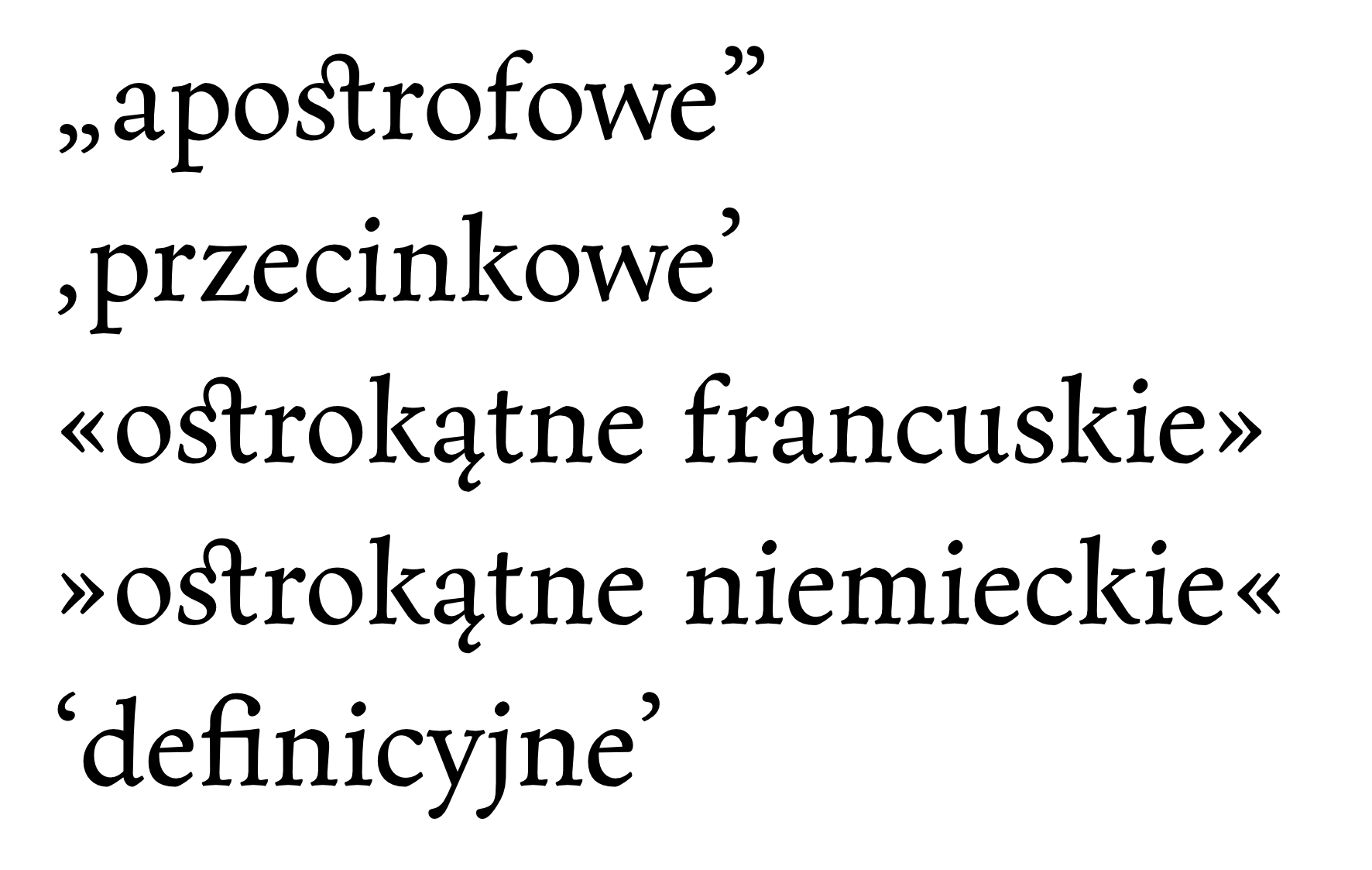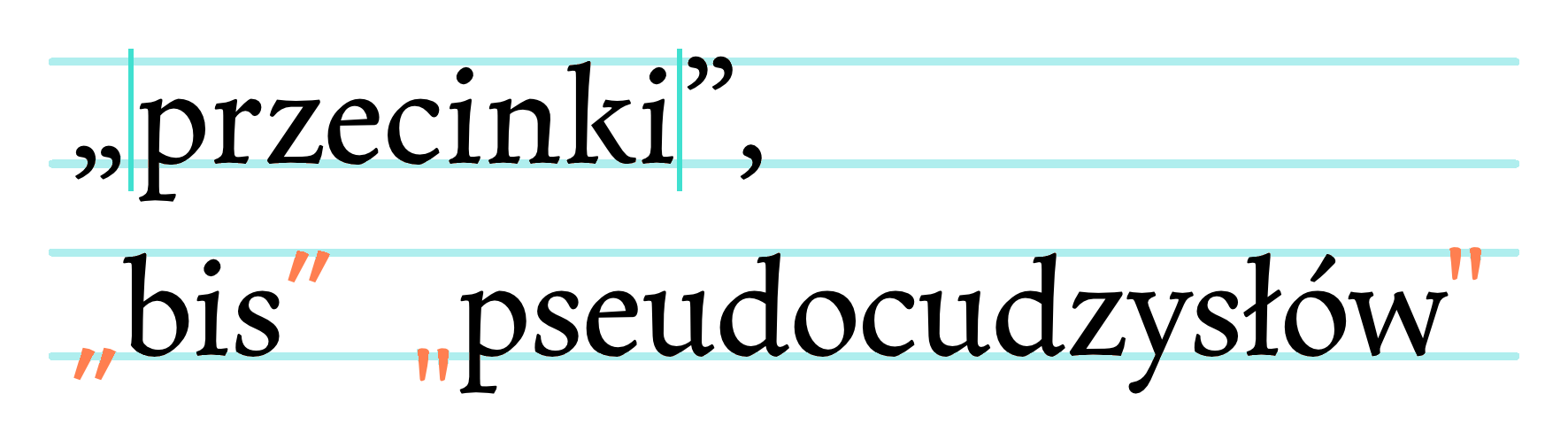
W polskich tekstach najczęściej spotyka się następujące rodzaje cudzysłowów:
Cudzysłowy apostrofowe. Są zalecane do używania jako cudzysłowy podstawowe. Jednak niektórzy typografowie uważają, że jeżeli cudzysłowów apostrofowych jest dużo obok siebie (np. dużo krótkich wyrazów objętych cudzysłowami), to nie wygląda to zbyt estetycznie. Dlatego dopuszczalne jest używanie jako cudzysłowów postawowych cudzysłowów ostrokątnych niemieckich.
Cudzysłowy przecinkowe. Składają się z przecinka jako cudzysłowu otwierającego i przecinka frakcji górnej (apostrofu) jako cudzysłowu zamykającego. Cudzysłowy przecinkowe były używane jako cudzysłowy drugiego stopnia, to znaczy jako cudzysłowów umieszczane w tekście już objętym cudzysłowami. Współcześnie cudzysłowy przecinkowe praktycznie nie są używane.
Cudzysłowy ostrokątne francuskie. Są używane do wyodrębniania znaczeń (w pracach naukowych i słownikach) i do wyodrębniania partii dialogowych i przytoczeń (głównie w utworach poetyckich).
Cudzysłowy ostrokątne niemieckie. Są używane jako cudzysłowy drugiego stopnia lub jako cudzysłowy podstawowe (w zastępstwie cudzysłowów apostrofowych).
Cudzysłowy definicyjne. Zwane są także łapkowymi i są używane do wyróżniania definicji znaczeniowych wyrazów i połączeń wyrazowych.
Różne rodzje cudzysłowów
Postać graficzna cudzysłowów
Prawidłową postacią graficzną cudzysłowów apostrofowych są dwa przecinki jako cudzysłów otwierający i dwa przecinki we frakcji górnej jako cudzysłów zamykający. Natomiast nieprawidłową postacią graficzną cudzysłowów apostrofowych jest znak bis (oznaczający cale i sekundy kątowe) czy pseudcudzysłów (pozostałość po cudzysłowie ze standardu ASCII).
Pomiędzy cudzysłowy (każdy ich rodzaj) a tekst można wstawić spację włoskową
Prawidłowe i nieprawidłowe cudzysłowy apostrofowe
Eliminowanie i zastępowanie cudzysłowów
Geoffrey Dowding [Finer Points in the Spacing & Arragement of Type ] uważa, że cudzysłowy zmniejszają czytelność tekstu w którym są używane. Jeśli tylko jest to możliwe powinny być eliminowane lub zastępowane innymi środkami wyrazu. Na podobnym stanowisku stoją: Jan Tschichold [The Form of the Book: Essays On the Morality of Good Design], Robert Bringhurst [The Elements of Typographic Style] czy Andrzej Markowski [Nowy słownik poprawnej polszczyzny PWN].
W przypadku przytaczania tytułów książek, artykułów, utowrów, rozdziałów, nazw dzieł artystycznych czy statków można użyć kursywy, natomiast tytuły gazet i czasopism należy pozostawić w cudzysłowach (np. »We wczorajszej „Przyjaciółce” ukazał się artykuł Pierwsza fala.«). Kursywą można także składać cytaty (np. »Nigdy czegoś takiego nie widziałem! – wykrzyknął Marek.«). W przypadku, gdy cytat występuje po dwukropku, a koniec cytatu da się jednoznacznie wskazać, cudzysłowów czy kursywy można w ogóle nie stosować (np. »Autorem słów: Oto skutki znajomości kobiet z poezji! jest Bolesław Prus.«).